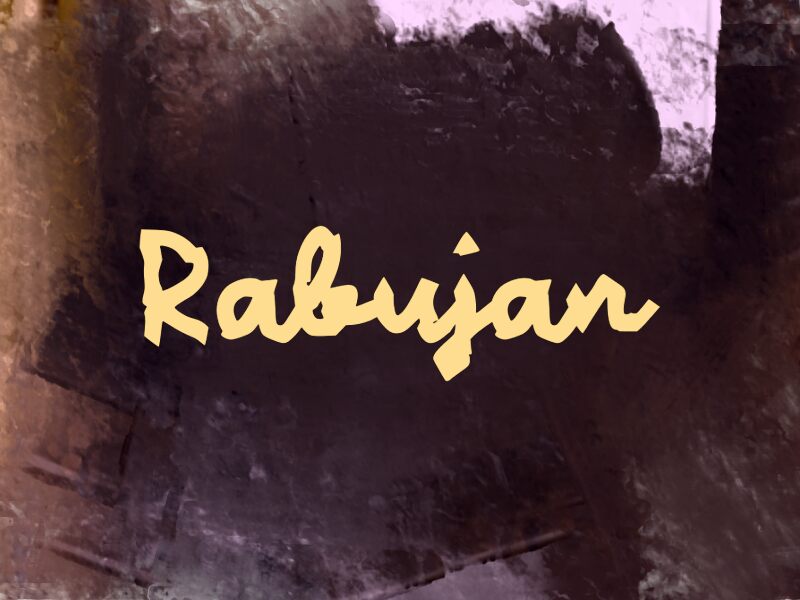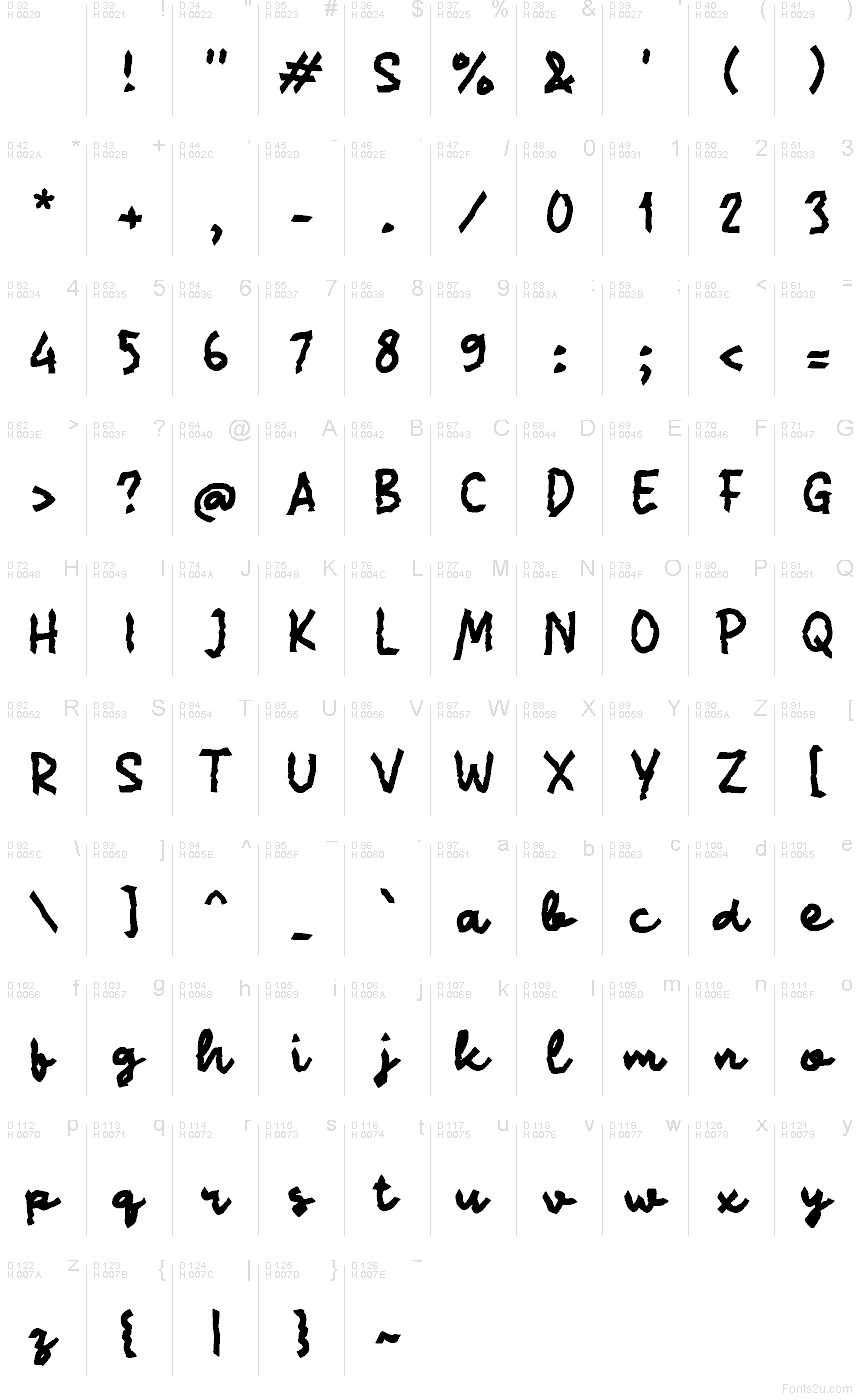
Rabujan
Rabujan di Wep è un font script a pennello gratuito con un dinamismo rapido, dipinto a mano e l'energia graffiante di un'insegna di strada. Le lettere sembrano cariche d'inchiostro, con un gioco che alterna tratti larghi e tagli netti; le giunzioni ad anello e le terminazioni a punta mantengono le parole in continuo movimento, evitando la rigidità della calligrafia tradizionale.
Questo font gratuito è perfetto per poster, copertine di album, branding di locali, packaging e grafiche social in cui un tocco grezzo e scritto a mano risulta più autentico di una scrittura troppo levigata. È ideale anche per titoli brevi, copertine e citazioni in evidenza: i tratti spessi e i movimenti veloci donano forza espressiva anche a testi minimi, con un gesto pittorico di grande impatto.